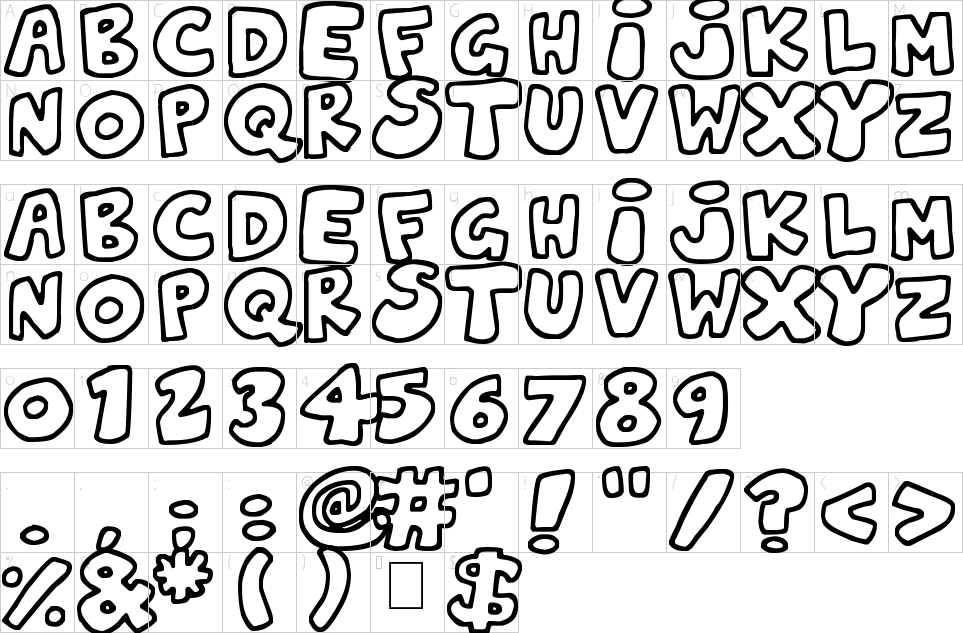
Descobrir uma nova fonte para seu próximo projeto pode ser um desafio, mas uma vez que você encontra a certa, o resultado pode ser surpreendentemente agradável. Essa é a essência da font Jelly Wobblers, uma oferta gratuita e extremamente versátil disponível para você. Desenvolvida pelo designer desconhecido Darrell Flood, essa font oferece um toque único ao seu design. O nome “Jelly Wobblers” se refere a suas formas molhadas e em movimento, que trazem um toque alegre e descontraído à sua interface. Ficou interessado? Descubra o que a Jelly Wobblers pode fazer para tornar o seu design mais atraente e agradável aos olhos. Com 2.834 downloads, essa font é uma escolha confiável e uma ótima adição à sua coleção de recursos gráficos gratuitos. Descarregue agora e veja o que ela pode fazer por seu próximo projeto.